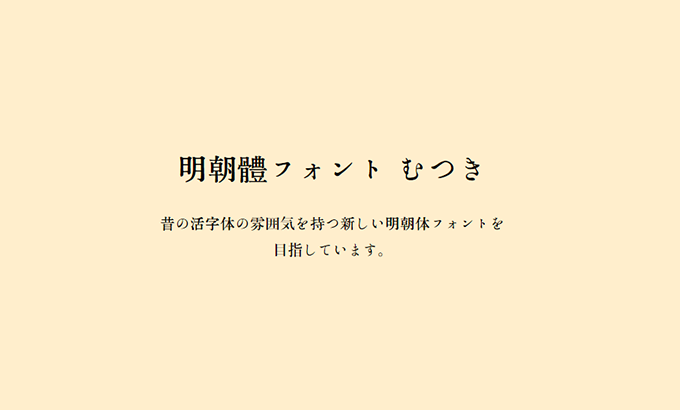
明朝體フォント むつき 2019.03.24 2017.01.27明朝體フォント むつきは、「GL-築地五号」をベースに製作された、昔の活字体の雰囲気を持つ新しい明朝体フォントです。ライセンス無料で使える商用可のフリーフォントです。ダウンロード明朝體フォント むつき当サイトはフリーフォントの紹介サイトです。フォントを利用の際には、各サイトで最新の利用条件やライセンスを必ず確認してください。フォント情報ライセンス商用可カテゴリー日本語 > 明朝体タグレトロ、スタンダード